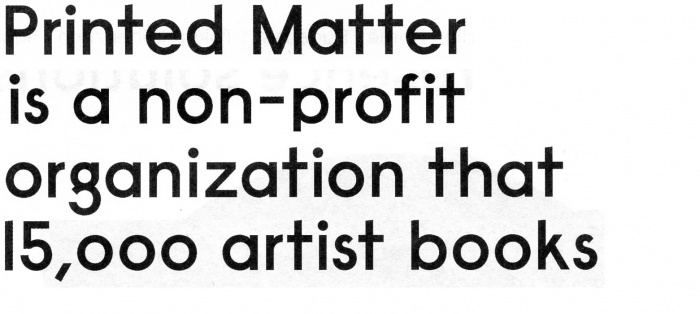
Hat jemand eine Idee? Das schräg oben angeschnittene "t", das "s", das "g" ..
Ist aus einer Anzeige von Printed Matter (http://printedmatter.org/). Ich werd die mal fragen, gute Idee.
Ansonsten: Die Modular geht in die richtige Richtung, aber bei der andern sind die Ober- und Unterlängen kürzer, das "f" zB ist auch anders ..
Ein Screenshot aus einem pdf? Dann dort hineinschauen.
Nie und nimmer ist es eine andere.
Rainer meinte, dass das Rätsel doch schon gelöst wäre, da es sich um die die Raisonne handelt. Ich habe ihn darin bekräftigt. Er hat nur versehentlich seinen Beitrag in den Orkus geschoben.